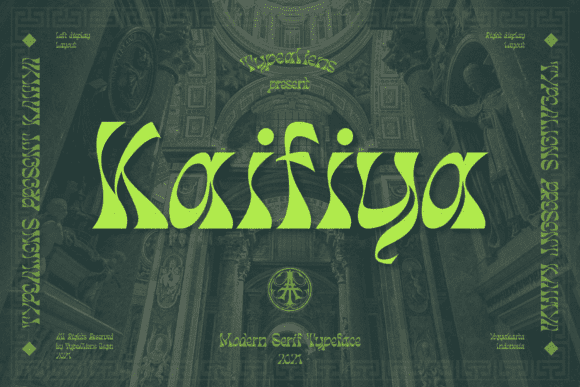
Kaifiya - классный, интересный и современный шрифт.
Этот шрифт отличается аккуратностью и высокой детализацией.
Независимо от темы, этот шрифт станет прекрасным дополнением к вашей библиотеке шрифтов, поскольку он способен улучшить любое творение.